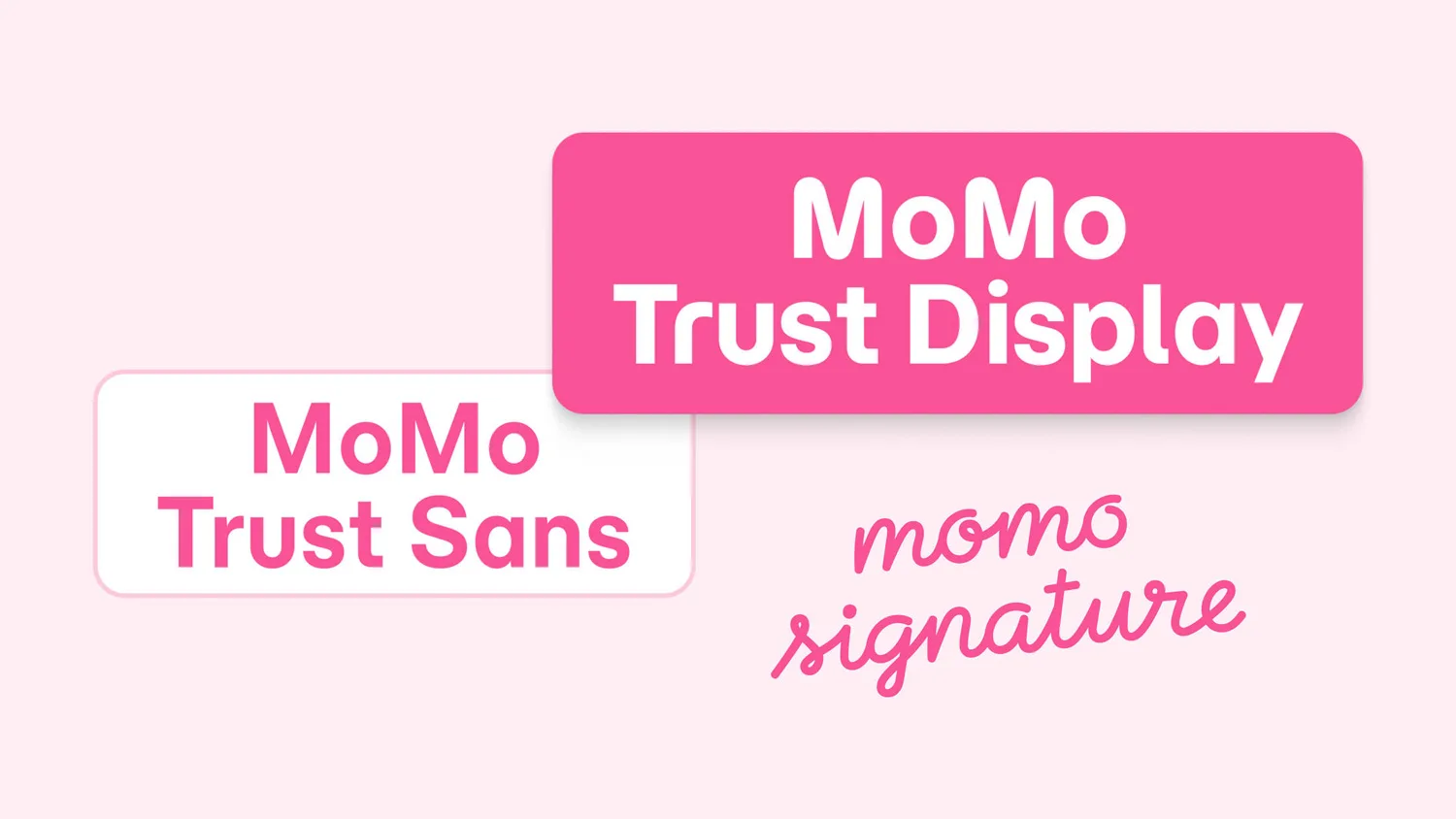
Font MoMo chính thức là bộ phông chữ được thiết kế độc quyền cho siêu ứng dụng MoMo với tên gọi MoMo Trust (bao gồm MoMo Trust Display và MoMo Trust Sans). Với cấu trúc bo tròn hiện đại, vững chãi và cực kỳ thân thiện, bộ phông chữ này giúp truyền tải thông điệp về sự tin cậy và minh bạch của một nền tảng tài chính. Doozypack.vn chia sẻ link MoMo font download chuẩn, hỗ trợ đầy đủ tiếng Việt để bạn thực hiện các dự án thiết kế bao bì tích hợp mã thanh toán hoặc bộ nhận diện thương hiệu startup chuyên nghiệp.
Đặc điểm thiết kế của bộ font chữ MoMo (MoMo Trust)
Bộ phông chữ MoMo Trust được tinh chỉnh tỉ mỉ để tạo ra sự đồng nhất trên cả giao diện ứng dụng di động lẫn các ấn phẩm in ấn quảng cáo ngoài trời.
Phong cách bo tròn hiện đại và đáng tin cậy
Đặc trưng lớn nhất của font chữ MoMo là các góc chữ được bo tròn mềm mại, tạo cảm giác vô cùng thân thiện và dễ tiếp cận. Khác với các dòng phông chữ hình học cứng nhắc, MoMo Trust mang lại sự cân bằng giữa tính kỹ thuật và cảm xúc nhân văn. Cấu trúc nét chữ dứt khoát kết hợp với các đường cong mịn màng giúp thương hiệu toát lên vẻ uy tín (Trust), rất phù hợp với lĩnh vực công nghệ và tài chính số.
Sự khác biệt giữa MoMo Trust Display và MoMo Trust Sans
Hệ gia đình MoMo font được chia thành hai nhánh chính để tối ưu hóa công năng hiển thị:
- MoMo Trust Display: Có cấu trúc chữ sắc sảo, thường dùng cho các tiêu đề lớn, banner hoặc Logo để tạo ấn tượng thị giác mạnh mẽ.
- MoMo Trust Sans: Được tối ưu hóa cho nội dung văn bản dài, hướng dẫn sử dụng hoặc bảng biểu, đảm bảo độ dễ đọc cực cao ngay cả ở kích thước nhỏ.
| Phiên bản Font | Đặc điểm thị giác | Ứng dụng đề xuất tại Doozypack.vn |
| MoMo Trust Display | Vững chãi, bo tròn | Dùng làm tiêu đề hộp quà, tiêu đề chính trên website. |
| MoMo Trust Sans | Cân đối, dễ đọc | Dùng cho bảng thành phần, địa chỉ sản xuất trên vỏ hộp. |
Gợi ý lựa chọn: Nếu bạn thiết kế bao bì có tích hợp mã QR thanh toán MoMo, hãy sử dụng font MoMo trust sans cho phần hướng dẫn thanh toán. Độ minh bạch của nét chữ giúp khách hàng dễ dàng quét mã và đọc các bước thao tác mà không bị nhầm lẫn.
03 Ứng dụng của font MoMo trong thiết kế bao bì tại Doozypack.vn
Vẻ đẹp hiện đại và uy tín của font chữ của MoMo mang lại hiệu quả thị giác đặc biệt trên các ấn phẩm thực tế:
- Túi giấy tích hợp mã QR: In hướng dẫn thanh toán bằng font MoMo lên túi giấy Ivory cán màng mờ giúp shop trông chuyên nghiệp và bắt kịp xu hướng thanh toán không tiền mặt.
- Hộp sản phẩm công nghệ (Fintech): Sử dụng font momo trust display cho tên dòng sản phẩm tạo cảm giác hiện đại và đẳng cấp.
- Tem nhãn dán thông minh: Cấu trúc rõ ràng của MoMo Sans giúp các thông tin chi tiết trên tem decal trở nên dễ tra cứu và thẩm mỹ hơn cho người tiêu dùng.